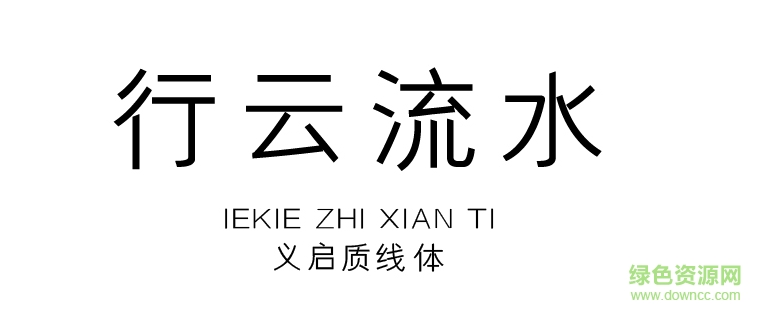
義啟質(zhì)線體是一款非常漂亮的字體,這款字體字形清秀,整體效果非常出色,比較適用于美術(shù)設(shè)計(jì)、藝術(shù)設(shè)計(jì)、海報(bào)廣告設(shè)計(jì)等領(lǐng)域,喜歡的朋友可以來綠色資源網(wǎng)下載使用喲!
義啟質(zhì)線體是繼宋體之后又一重要印刷字體。它與宋體結(jié)構(gòu)相同,但點(diǎn)畫粗壯且粗細(xì)一律,起止皆方,氣象豐滿。作者通過對(duì)等線體的認(rèn)真分析,線條的對(duì)比調(diào)試,字體空間的分配,色彩度的感應(yīng)變化及字體視覺真實(shí)與假象的運(yùn)用,并且結(jié)合黑體與宋體的特點(diǎn)與理解,最終設(shè)計(jì)出這款“義啟質(zhì)線體”。 義啟質(zhì)線體, 筆畫質(zhì)感十足,簡(jiǎn)約